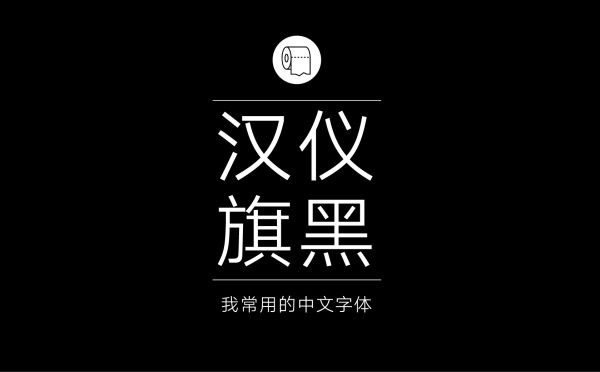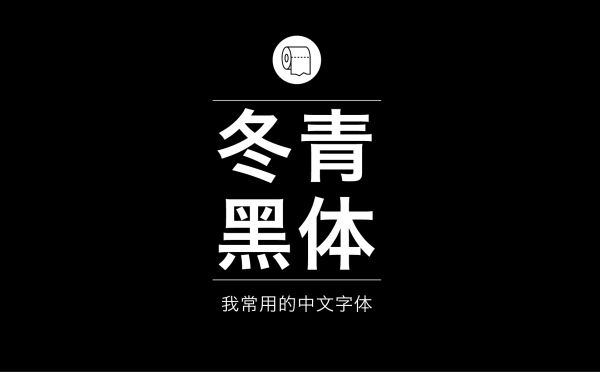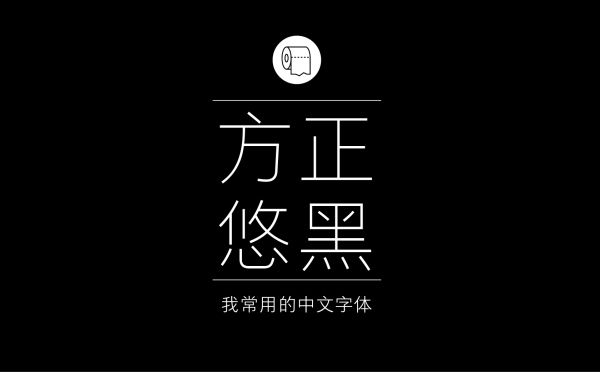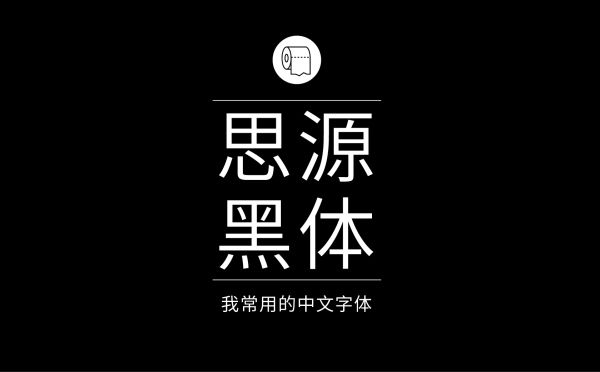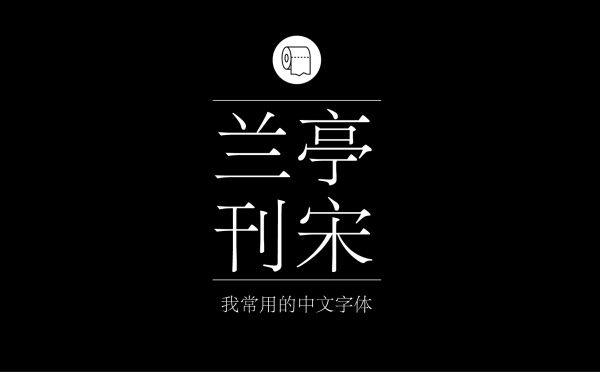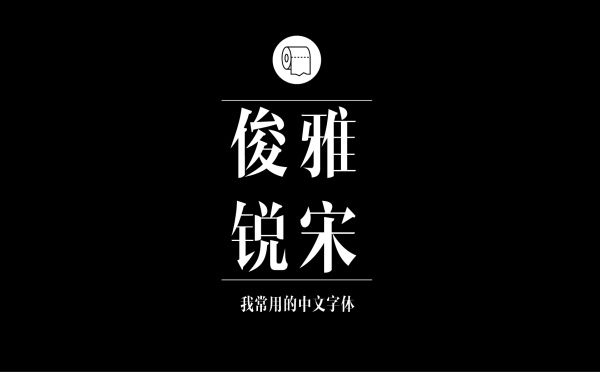
耐看好用!专业平面设计师常用的那些中文字体
1. 精致黑体字型
△  汉仪旗黑
△  冬青黑体简体中文
△  方正兰亭黑简体 (方正最火的黑体系列之一,现代感很强的黑体字)
△  方正悠黑 (我个人非常喜欢的一套,笔画字型都很精致)
△   思源黑体 ( 我本人用的最多的字体,因为易用耐看,而且是免商用!)
2. 优美宋体字型
△   方正书宋简体
△  方正兰亭刊宋
△  思源宋体(前段时间刷遍朋友圈的字体,以后宋体字不用愁)
△  造字工房俊雅锐宋(造字工房这套字强化了宋体“横细竖粗”的特点,同时又去掉了笔末装饰,让这套字体整体感既有设计感,又不失传统韵味。)
△   造字工房言宋
3.现代美术字型
△   文悦新青年体(这套简直就是网红字体,应该是近期最火爆的一款,适用性很强,特别是用在海报,banner等设计上,像奇葩说这些综艺用的也是这套字体。)
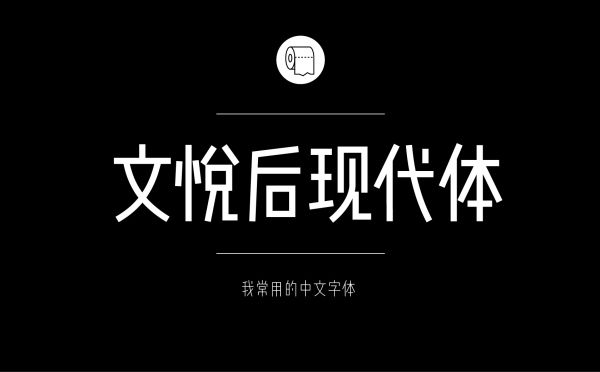
△   文悦后现代体(文悦科技这两套字体我个人都特别喜欢,设计感很强的美术字体)
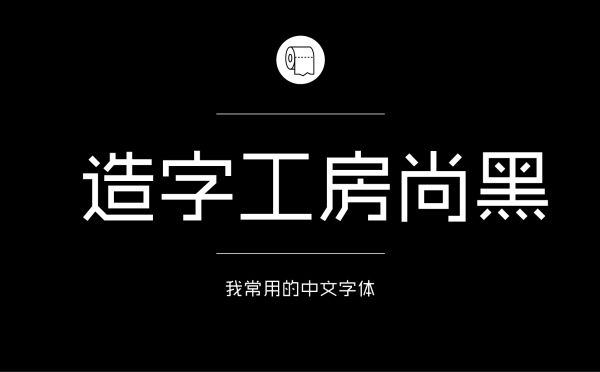
△  造字工房尚黑(造字工房早期的字体)
△   锐字逼格青春体(虽然字体名字有点low low的,但是有时候会用得上这类字型)
△   GD-高速道路ゴシック(这套是日本字体包,但里面有很多汉字可以借鉴,日本字体的字型处理总有一种独特的味道。)
4. 韵味复古字型
△  方正清刻本悦宋简体(曾经很喜欢这一类的刻本的字型,还有另一套爆款:康熙字典体,正因为这两套的影响才有了后面设计“燕安字”的想法。)
△  文悦古体仿宋 (我一直都有在研究如何将仿宋的字型现代化,文悦这套字做的是很不错的,很有味道。)
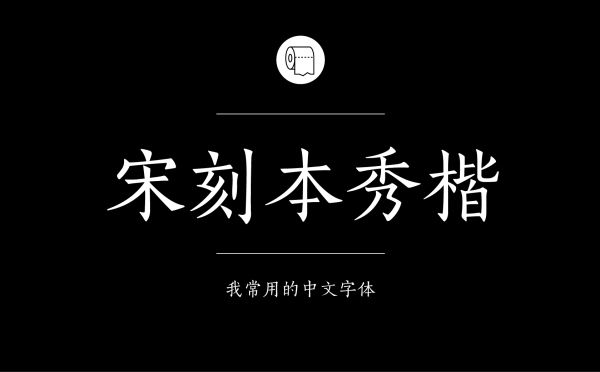
△   方正宋刻本秀楷简体
△  造字工房黄金时代 (这套字体很有明国时期的复古感。)
△  字酷堂黄自元楷体
5. 传统书法字型
△   叶根友刀锋黑草(叶根友的系列字体中我比较喜欢这一套,挺有气势的。)
△  李旭科书法(书法在日常的版式中我比较少用到,个人更多的是在学习书法的起笔落笔等,对我做标志设计有很大帮助。)
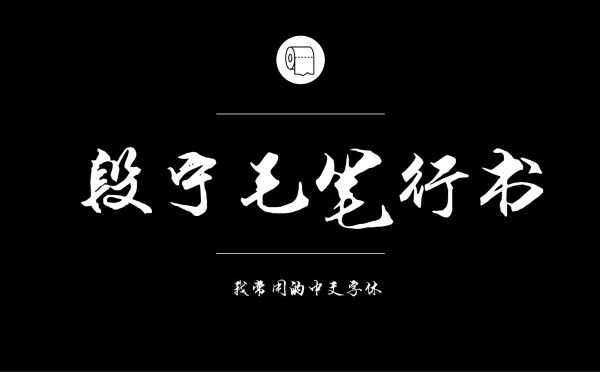
△  段宁毛笔行书
6. 日式毛笔字型
△   味わい毛筆(日本的毛笔字库比国内的多很多,很多字型都值得参考学习。)
△  京円
△  白舟行書教漢
△  大髭